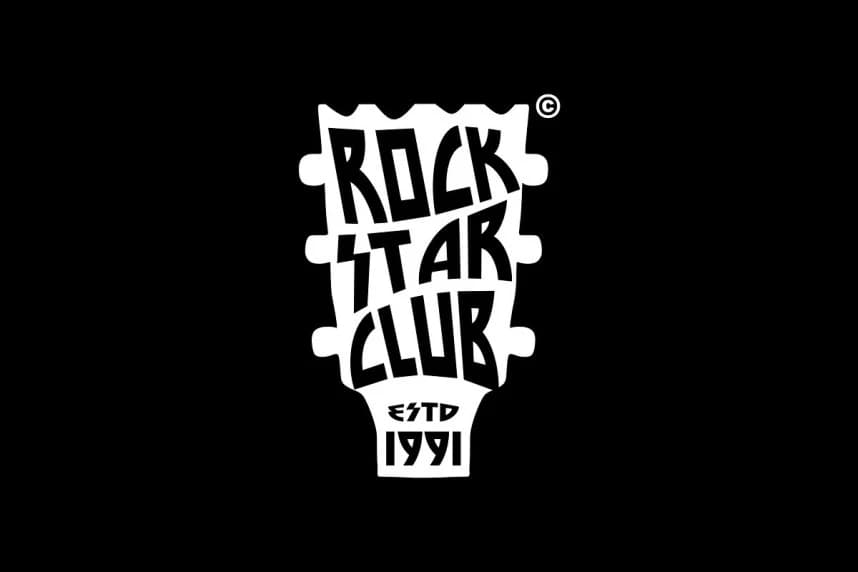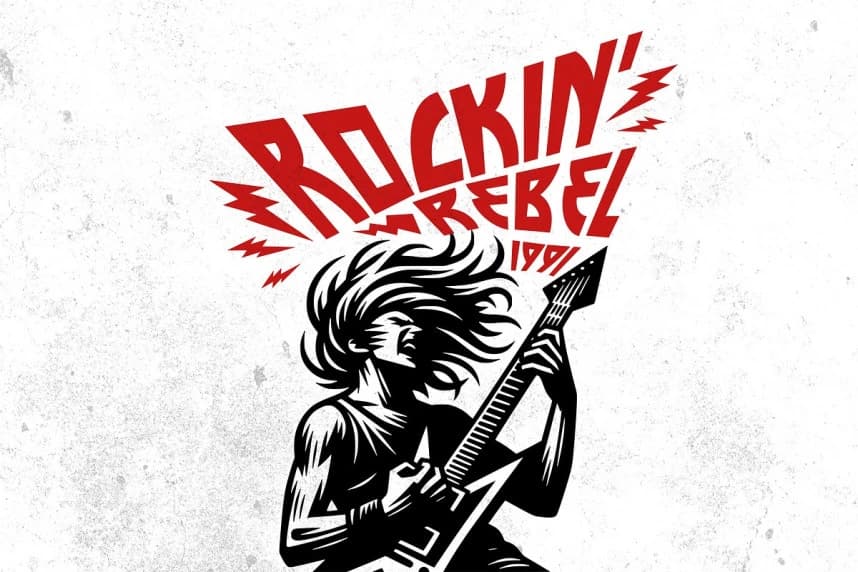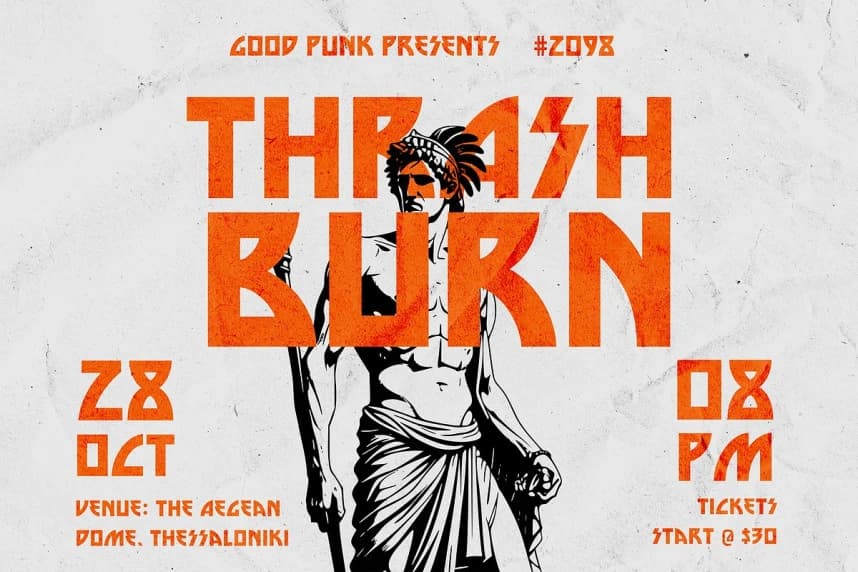
Thrash Burn Font
Thrash Burn Font, punk rock, isyan ve yeraltı sertliğinin ateşlerinde şekillenmiş, 1980'lerden ilham alan keskin bir yazı tipi. Bu sıradan bir retro fontu değildir; bu, daha gür ve sert bir dönemin skateparklerinden, dive barlarından ve anarşist zine'lerinden yükselen tam gaz bir haykırış.
Thrash Burn Font, punk rock'ın isyanı ve yeraltı sertliğinin ateşinde biçimlenen, 1980'lerden ilham alan sivri bir tipografi. Bu sıradan bir retro font değil; daha gür ve sert bir çağın skateparklarından, loş dive barlardan ve anarşist zine'larından yükselen tam gaz bir bağırış.
Thrash Burn